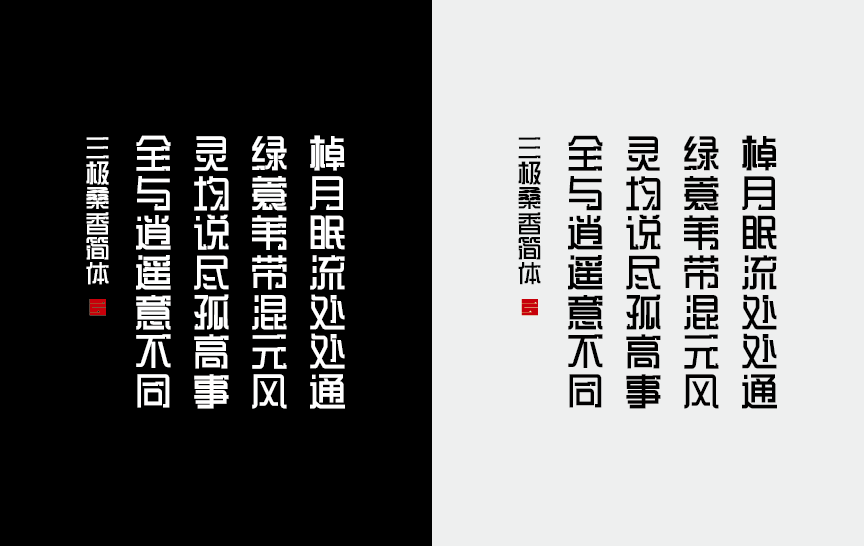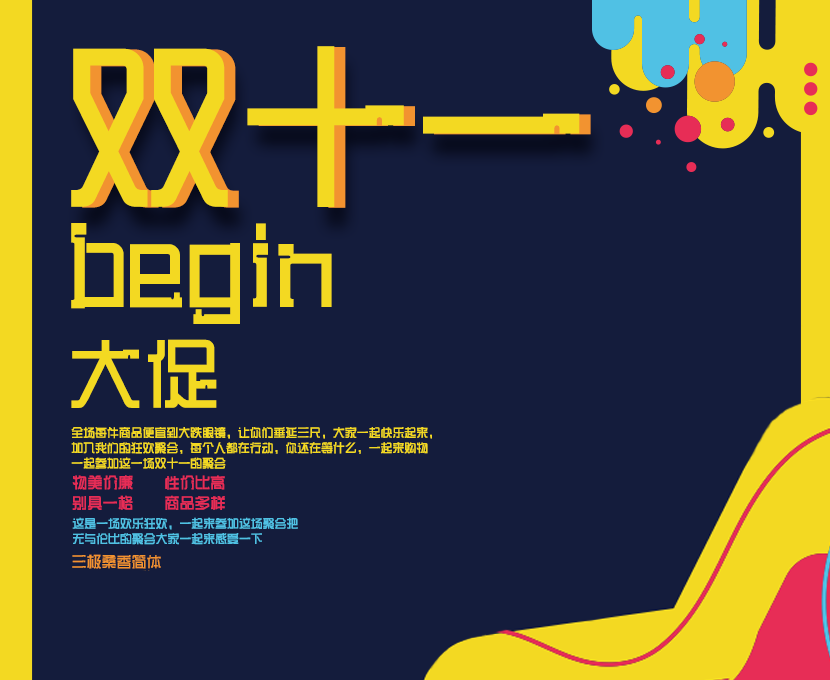
三极桑香简体
住处近山常足雨
三极桑香简体是一款装饰意味浓厚的创意字体。这款字弱化了笔画中大部分的弧线,笔画的右方统一做了圆角处理,将横、竖和勾设计别样的圆口留白,另外勾增加了方块的小设计,大胆创造,又不失文字的识别性。
带有异域风情的独特,字形稳定坚实,适用于品牌广告、产品包装设计和建筑行业应用。
适用媒介:报纸、杂志、书籍、广告、宣传册、包装、影视、屏幕显示、交互设计。